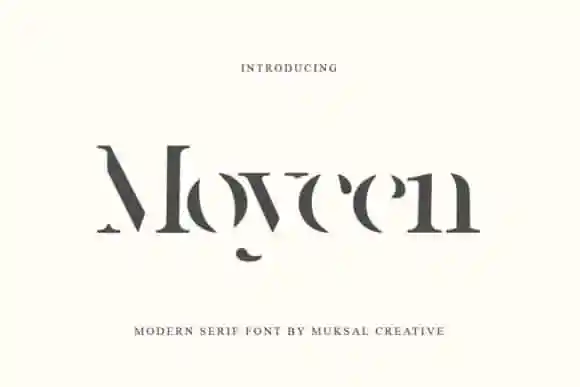
Moycen Display Font – Download Grátis
A Moycen Display Font é perfeita para quem busca uma sensação moderna e sofisticada em suas criações digitais. Desenvolvida pelo designer de fontes Muksal Creative, ela traz a essência do ser humano na sua linguagem elegante e distinta. Com seus traços serifados que celebram formas abstratas com todo seu encanto único, essa fonte moderna enriquece qualquer projeto visual. Seja para um design convencional ou algo mais inovador, a Moycen Display não deixará seu trabalho imerso apenas na superfície; ao contrário, ela o fará pulsar e viver em cada detalhe. Inclua esta fonte em seus trabalhos de design e observe como ela dota suas ideias favoritas de vida, beleza e movimento.